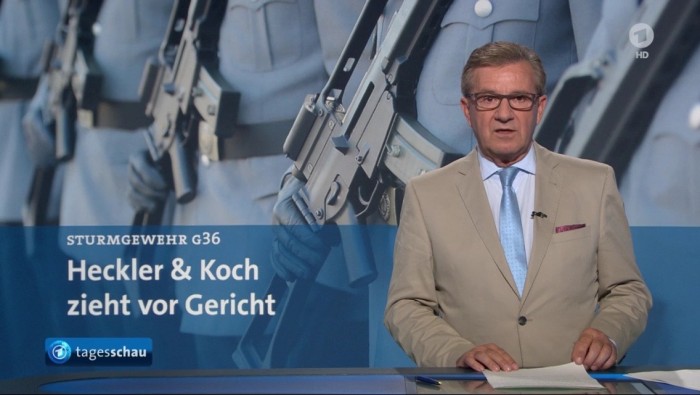
Verwendung von Mediävalziffern und Versalziffern
Bisher habe ich es so verstanden, dass in einem Fließtext Mediävalziffern, aufgrund deren besserer Eingliederung in den Text, gesetzt werden und in Tabellen Versalziffern gesetzt werden.
Mehrere Fragen habe ich noch:
Wie würdet ihr die Ziffern bei einem wissenschaftlichen Text mit vielen Zahlen, die z.B. Konzentrationenen oder Temperaturen angeben, setzen?
Wie würdet ihr die Jahreszahlen von Zitaten im Text setzen?
Wie sieht es mit Seitenzahlen und Kapitelüberschriften aus? Die Kapitelüberschriften wurden in einer Sans Serif gesetzt.
Das sind typografische Entscheidungen, die immer im Einzelfall vom Entwerfer neu bedacht, begründet und getroffen werden und hängt auch von den verwendeten Schriften und vom Satz ab. Ich selbst verwende Versalziffern nur selten, in Versalzeilen beispielsweise, wenn die Ziffern nicht auffallen sollen. Mit Serifen und Textsorten hat diese Frage nichts zu tun. Man kann auch in Tabellen Minuskelziffern setzen. Und in manchen Schriften gibt es auch Versalziffern in Kapitälchenhöhe.
Vielleicht so ein paar Gedanken zu den angegebenen Fällen:
Wenn Du davon ausgehst, dass jemand die Zahlen in Tabellen vollständig lesen möchte (eher unwahrscheinlich), sind vermutlich Mediävalziffern zur Lesereleichterung besser. Wenn es hingegen wichtiger ist, dass der Leser die Tabellenstruktur erkennt, sind Versalziffern besser, da sie die Struktur nich durchbrechen. In jedem Fall solltest Du darauf achten, dass Du Tabellenziffern, d. h. dicktengleiche Ziffern nutzt.
Für wissenschaftliche Zahlen würde ich nur Mediävalziffern verwenden, wenn sie kaum oder gar nicht in Formeln auftauchen, da sie sich für den Formelsatz nicht eignen. Auch dann kann es sinnvoll sein, Versalziffern zu verwenden, nämlich wenn Du möchtest, dass Ziffern herausstechen und schnell auffindbar sind (ich habe mich hier etwas ausführlicher darüber ausgelassen). Beachte, dass Du hier konsistent sein und wenn, dann für alle derartigen Zahlen Mediävalziffern verwenden solltest.
Jahreszahlen von Zitaten im Text sind ein typischer Fall für Mediävalziffern, da Du sie wahrscheinlich für Nebensache erachtest und deshalb nicht möchtest, dass sie herausstechen.
Ob ich Seitenzahlen in Mediävalziffern setze, hängt davon ab, wie sie verwendet werden. Wenn sie alleine stehen oder in Verweisen im Fließtext würde ich wahrscheinlich Mediävalziffern verwenden; in Kopfzeilen mit Kapitelüberschriften in Versalien oder Kapitälchen würde ich Versalziffern einsetzen.
Ich würde dringend auch auf die Konventionen achten. In wissenschaftlichen Journalen werden, zumindest in the Biowissenschaften, fast ausschließlich Versalziffern für Temperatur- und Konzentrationsangaben verwendet. Ich verstoße gerne gegen diese Konvention, die Kollegen kommentieren dies allerdings immer, weil sie es als ungewöhnlich empfinden. Dies ist im Prinzip eigentlich auch richtig: gerade bei Konzentrationsangaben gibt es ein festes Regelwerk für die Angaben. »Molar« wird nun mal mit einem großen M abgekürzt, der Zusatz »milli« is hingegen klein, usw. usf. Zusammen mit Versalziffern gewöhnt man sich sehr schnell daran und mit Mediävalziffern liest es sich plötzlich sehr ungewöhntlich und wird auch, ob der Ober- und Unterlängen, sehr unruhig im Satzbild.
Zusammen mit Versalziffern gewöhnt man sich sehr schnell daran und mit Mediävalziffern liest es sich plötzlich sehr ungewöhntlich und wird auch, ob der Ober- und Unterlängen, sehr unruhig im Satzbild.
Weil CRudolph es gerade anspricht: Es ist auch ratsam, sich bei der Schriftwahl mit diesem Aspekt im Vorfeld zu befassen. Bei manchen Satzschriften fallen die Ober- und Unterlängen eher schwach aus, bei anderen sehr deutlich (und daher für manche Leser möglicherweise besonders störend bzw. ungewohnt) – geht meistens auch mit der x-Höhe des jeweiligen Fonts einher.
Vielen Dank schon einmal für Eure ausführlichen Antworten.
So einfach ist die Entscheidung dann doch wohl nicht. Ich nahm an, dass es dafür "Regeln" gibt oder dass es einen gängiger Stil gibt. So scheint es dann aber nicht zu sein, d.h. ich muss wohl selbst entscheiden welche Ziffern ich verwende.
Also ich finde die Mediävalziffern im Fließtext schöner. Allerdings verwendet z.B. Nature durchgehend Versalziffern. Die Ziffern tauchen nicht in Formeln auf, sondern nur im Text.
Die Schriftart habe ich allerdings schon ausgewählt, da habe ich mich ganz klassisch für die Minion entschieden. Aber für das nächste Projekt weiss ich dann schon einmal Bescheid, worauf man vorher achten muss!
Wäre es stilistisch daneben für den einen Zahlentyp (z.B. Jahreszahl) Mediävalziffern zu verwenden und für einen anderen typ (z.B. Konzentrationen, Temperaturen o.ä.) Versalziffern?
Ich vermute Du beziehst Dich auf Jahresangaben in Referenzen? Aus Anwender-Sicht geht in Referenzen im Prinzip fast alles, weil sie stilistisch ein Stolperstein sind. Das Konstrukt »(Autor et al., 2008)« wird immer aus dem Text hervorstechen. Und im Prinzip ist das auch richtig so, weil man sehr schnell diese Einheiten erkennt und überliest, es sei denn man möchte wissen auf welches Paper sich ein Autor bezieht. In einigen Journalen wird der Autorenname in Kapitälchen gesetzt, was diesen Effekt sogar noch verstärkt. In diesem Sinn würde ich im Sinne der Zielgruppe ausprobieren ob Jahreszahlen in Mediävalziffern die Referenzen nicht sogar zu stark im Text verschwinden lassen. In meiner Dissertation habe ich einen gemischten Ansatz gewählt: die Namen sind in Kapitälchen, die Jahreszahlen in Mediävalziffern. Alle anderen Ziffern im Text (Konzentrationen, Zahlen in Genbezeichnungen etc.) sind alle konsequent in Versalziffern.
Die Benummerung erleichtert natürlich dem Leser die Erfassung der Überschriften-Ebenen, also der Hierarchie. Wenn man nicht benummert, dann erfordert die typografische Gestaltung der Überschriften-Ebenen etwas mehr Arbeit, weil dies intuitiv erfassbar sein muß wenn Überschriften für sich alleine auf einer Seite stehen. Aber ansonsten lautet mein persönlicher Rat: Benummerung getrost einfach weglassen. Das braucht kein Mensch. :bandit: